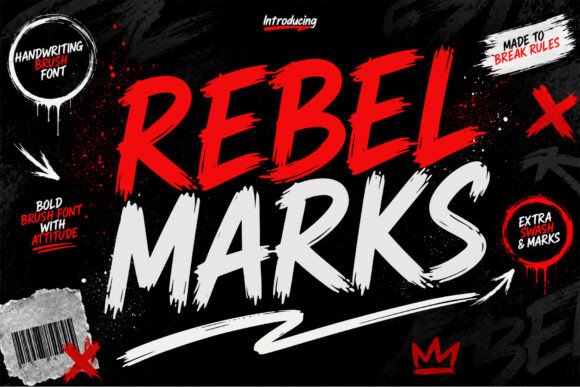
Rebel Marks
Jika anda sedang mencari aset berkualiti tinggi seperti Rebel Marks, pakej premium ini merupakan pilihan yang hebat untuk projek kreatif anda.
Sama ada anda mencipta produk POD (Print on Demand), jemputan perkahwinan atau grafik media sosial, Rebel Marks amat bersesuaian.